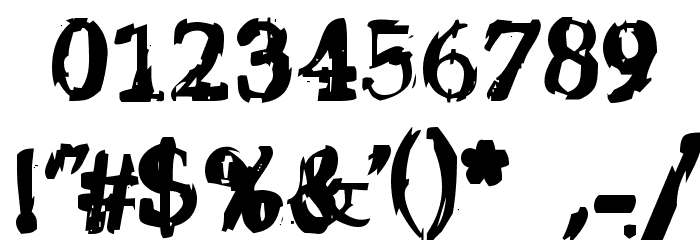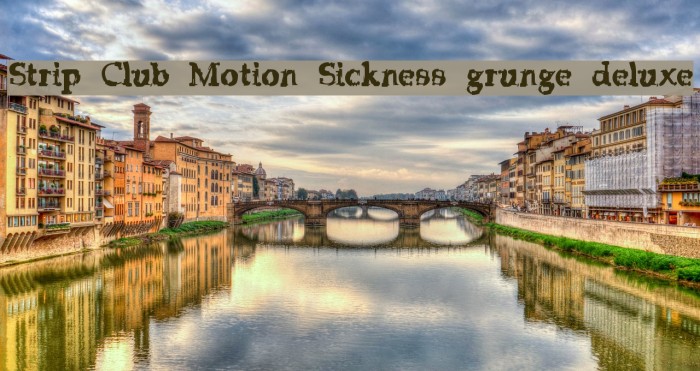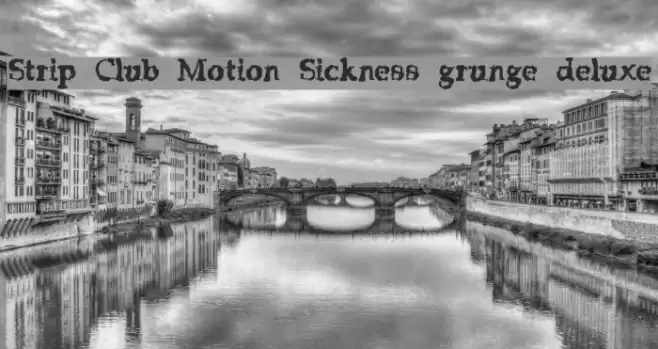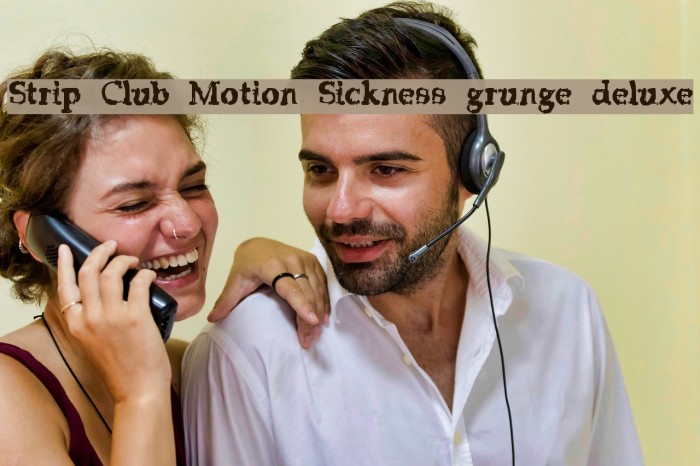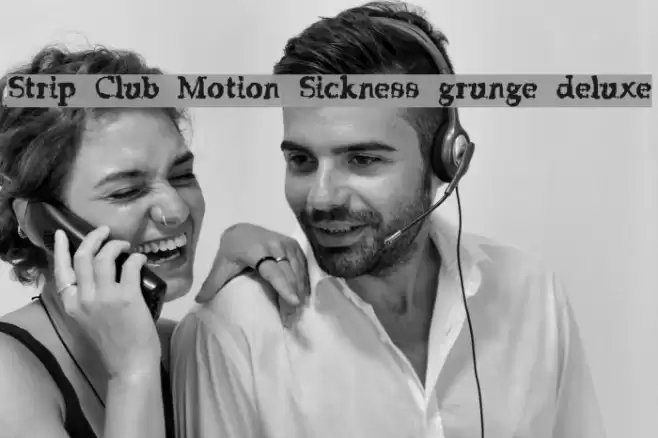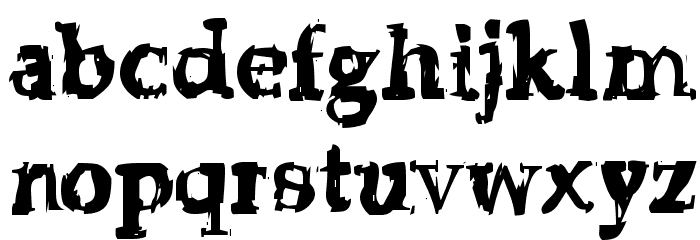
Strip Club Motion Sickness grunge deluxe Font
✎ Distorted Eroded
| Categorii | Distorted Eroded |
| Stil general | Grunge, Edgy |
| Proiecte propuse | Ideal for music album covers, edgy posters, streetwear branding, and any project requiring a bold, rebellious look. |